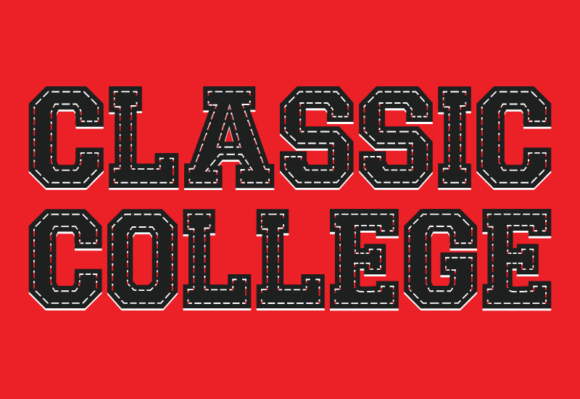
Classic College
Classic College – Un regard approfondi sur la police d’écriture sportive ultime
Classic College n’est pas simplement une police d’écriture ; c’est une véritable immersion dans la grâce nostalgique du sport universitaire américain. Conçue pour résonner avec l’esthétique « all‑American », elle combine un charme vintage à une énergie dynamique, idéale pour les logos de football, baseball ou basketball ainsi que pour les t‑shirts d’équipes.
Pourquoi choisir Classic College pour votre branding sportif ?
- Authenticité varsity : chaque glyphe rappelle les panneaux d’affichage des campus des années 50‑60, offrant un look immédiatement reconnaissable.
- Lisibilité optimale : les caractères gras et bien proportionnés garantissent une visibilité parfaite, même à petite taille ou sur des supports imprimés.
- Polyvalence : que vous créiez un logo de football, un maillot de baseball ou un design de basket‑ball, la police s’adapte à tous les médias (impression, web, textile).
- Esprit de compétition : le style audacieux transmet la détermination et le « winning spirit » propre aux équipes universitaires.
Points forts et limites
Points forts : esthétique rétro, forte identité visuelle, excellente lisibilité, adaptée aux projets sport et éducatifs.
Limites potentielles : moins adaptée aux projets très modernes ou minimalistes qui recherchent une typographie ultra‑sleek.
Conclusion – Un must‑have pour les marques sportives
Si votre objectif est de capturer l’essence même du campus américain et de projeter la passion du sport universitaire, Classic College est la police idéale. Elle combine charme intemporel et énergie dynamique, faisant de chaque logo ou design une véritable déclaration de victoire. N’attendez plus : intégrez Classic College à votre prochaine campagne et laissez le spirit de la varsity parler pour vous.